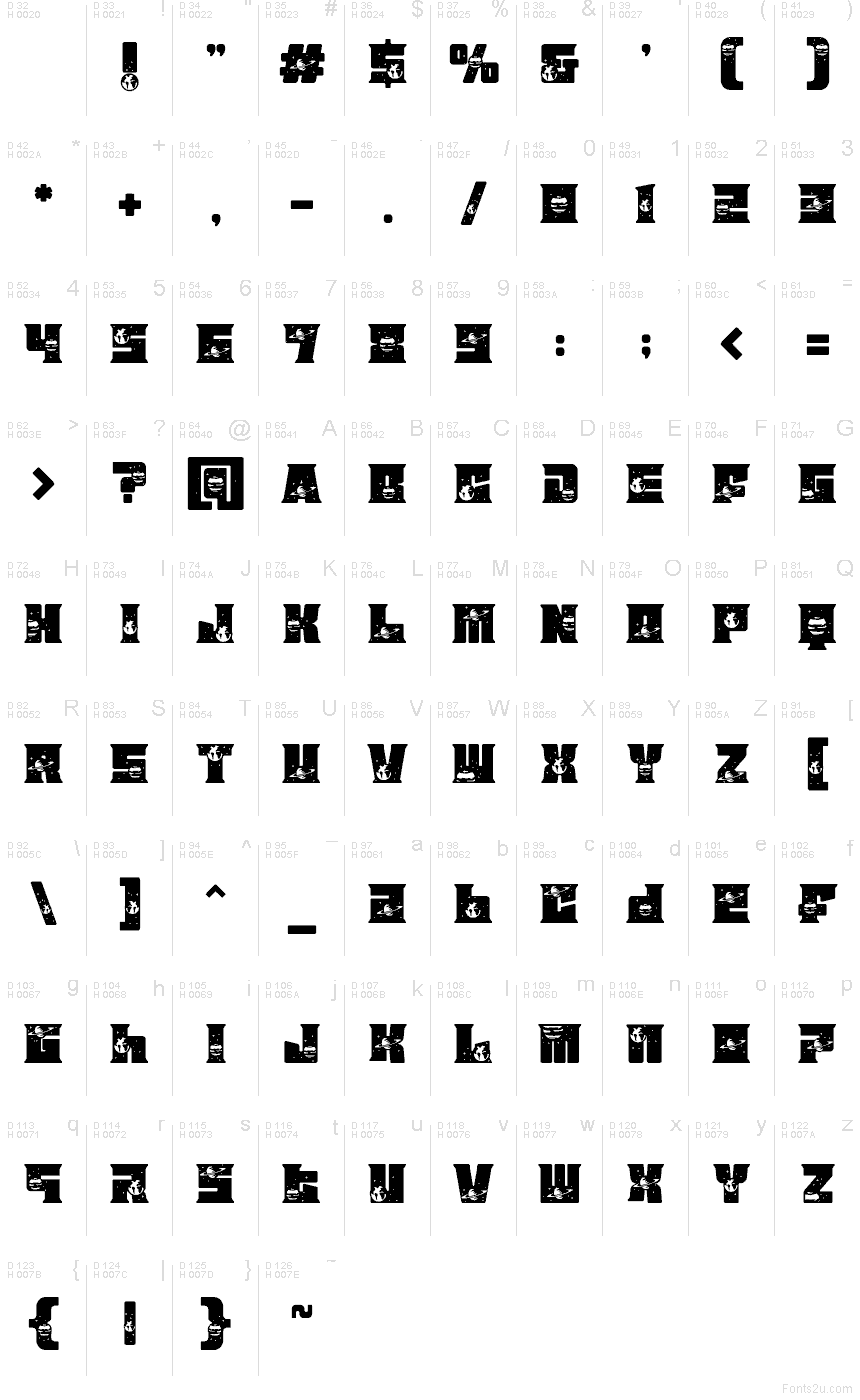
Astral Zenith Seven od Putracetol Studio je bezplatné písmo typu display s vesmírnou tematikou, které proměňuje písmena v pole vyřezaných siluet a levitujících kosmických detailů. Jeho masivní tvary jsou doplněny planetami, prstenci, hvězdami a motivy vesmírných lodí, což dává designu rytmus připomínající plakáty sci-fi, nikoliv jen obyčejnou dekoraci.
Díky tomu je to silná volba pro názvy her, pozvánky na akce, miniatury na YouTube, tematické obaly a dětské naučné materiály, kde musí vizuál vesmíru fungovat dříve než samotná slova. Krátké nadpisy, logo-experimenty a úvody sekcí těží z tohoto písma nejvíce, protože vnitřní scény dodávají každému slovu vlastní grafickou roli.
Astral Zenith Seven